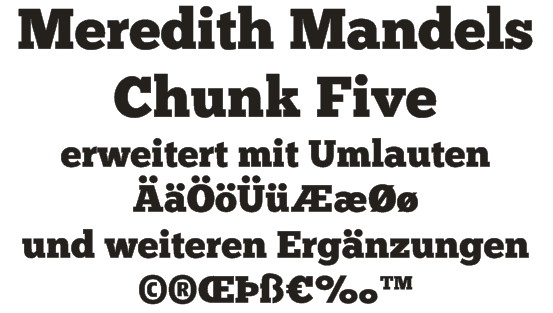
Europäische Studentenorganisation - Magazinschrift gesucht
Ich suche eine passende Schrift für ein Magazin (A4, zweispaltig); sowohl Fließtext als auch Head/Subhead-Schriften werden gesucht. Die Schrift sollte jung wirken und international.
Generell wäre ich euch auch dankbar, wenn ihr mir eure Meinung sagt zur Frage: Fließtext eher Serif oder Sanserif? Da es nicht soooo lange Artikel sein werden, liebäugele ich auch mit einer Sanserifen.
Diese hier finde ich schonmal sehr schick, zumindest für Überschriften:
Also um es genauer zu machen:
Ich suche eine Schriftart, die
- für kurze und mittlere Artikel in Magazinen geeignet ist, also keine Buchschrift.
- die nicht zu ernst oder alt wirkt (junge Studenten)
Ich habe mir als Überschrift diese hier ausgesucht: http://www.fontsquirrel.com/fonts/ChunkFive
Hier ist mal eine Probeversion einer Artikelseite:
Was die vorgeschlagene DIN Text Pro angeht: Die gefällt mir auch sehr gut. Ist es klug, sich dann zB nur die PF DIN Text Pro Thin und die zugehörige Italic zu kaufen?
Ich hab hier bereits dem lieben Neuzugang Uhu die Minion und Myriad sowie die PT Sans und PT Serif als kostenfrei verfügbare Schriften wärmstens ans Herz gelegt: gut ausgebaut, gut gezeichnet, gut zu gebrauchen :-D Minion und Myriad gibt es auch in Pro-Versionen, falls Du irgendwelche obskuren Zeichen brauchst, oder schmale Schnitte ...
Mit der PT Sans hab ich auch bereits experimentiert.. aber irgendwie taugt die mir nicht. Ich werd mal sehen, was ich mit den Klassikern machen kann (Minion, Myriad). Nur wollte ich diesmal auch etwas mehr ausprobieren, noch etwas unkonventioneller als die bekannten Schriften.
Di niente. Ja, der ist super, aber zu Rastern steht meiner Erinnerung nach nix drin, nur zu Seitenspiegeln :-D Na, so linear muss ein Raster nicht sein, nicht in dem Sinn, dass es einengt: Du konstruierst Dir ja, was Du brauchst :-D Aber ohne kannst Du so ein komplexes Layout, wie eine Zeitschrift das mit sich bringt, mit Rubriken, Miniartikeln etc. gleich knicken, das sieht aus wie bunter Hund ... ;-)
Zum Beispiel: League Gothic, Megalopolis, Mr Jones, Nikaia, Sensation, St Ryde
Eine Möglichkeit für den Fließtext wäre, wenn’s denn eine Grotesk sein soll, auch die Open Sans.
Ich würde aber eine Schraffenschrift verwenden, da ich die für besser lesbar halte. (Zum Beispiel Gentium oder Serif Beta). Da scheiden sich aber die Geister; Du kannst also nach Deinem Geschmack entscheiden.